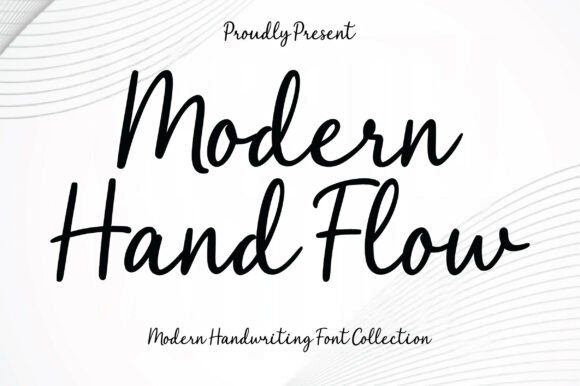
Modern Hand Flow
適切なデザイン要素を見つけるのは難しい場合がありますが、Modern Hand Flowは作品を即座に引き立てる優れたコレクションを提供します。
POD(オンデマンド印刷)製品、結婚式の招待状、またはソーシャルメディアのグラフィックを作成している場合でも、Modern Hand Flowは理想的です。